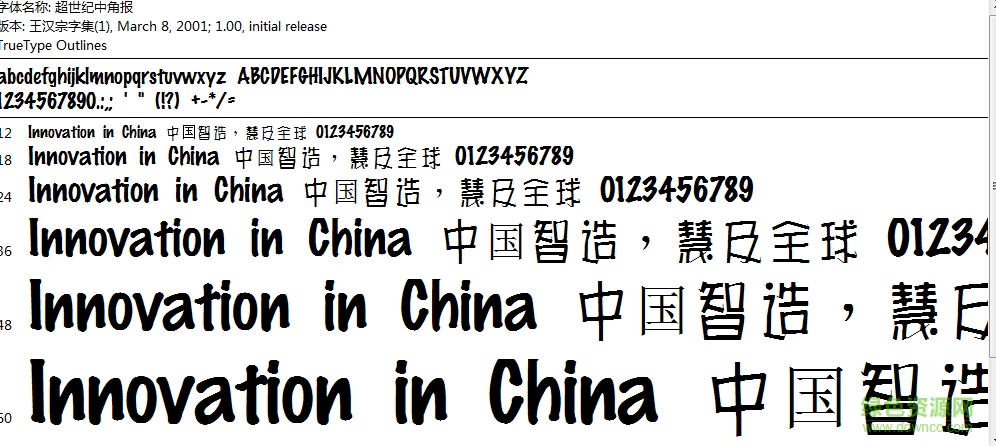
超世紀(jì)中角字體是一款體勻逼齊整、字體較籀文容易書(shū)寫(xiě)標(biāo)準(zhǔn)字體。這個(gè)字體打印出來(lái)十分的舒服,而且排版間隔都非常不錯(cuò),它非常受用戶(hù)們的喜歡,趕緊來(lái)綠色資源網(wǎng)下載糾正你的寫(xiě)字習(xí)慣吧!